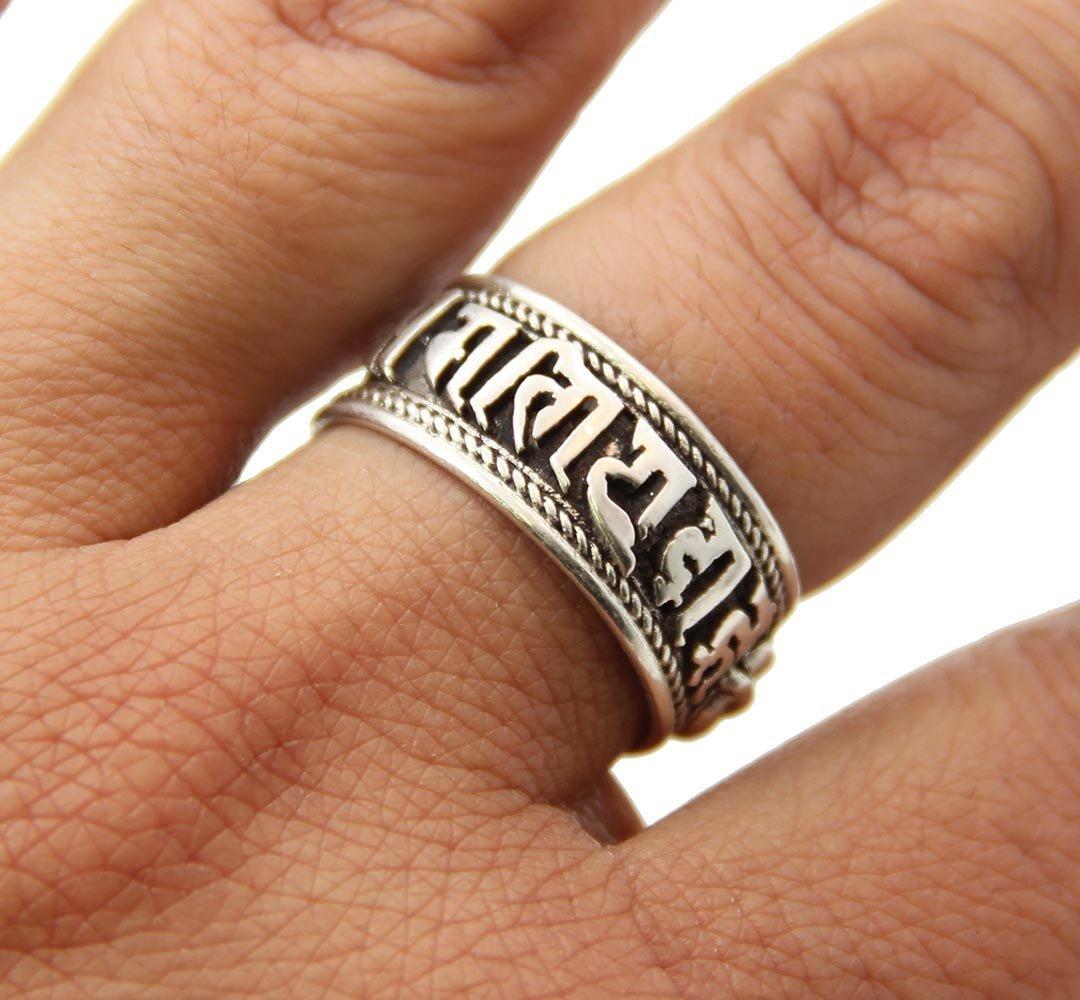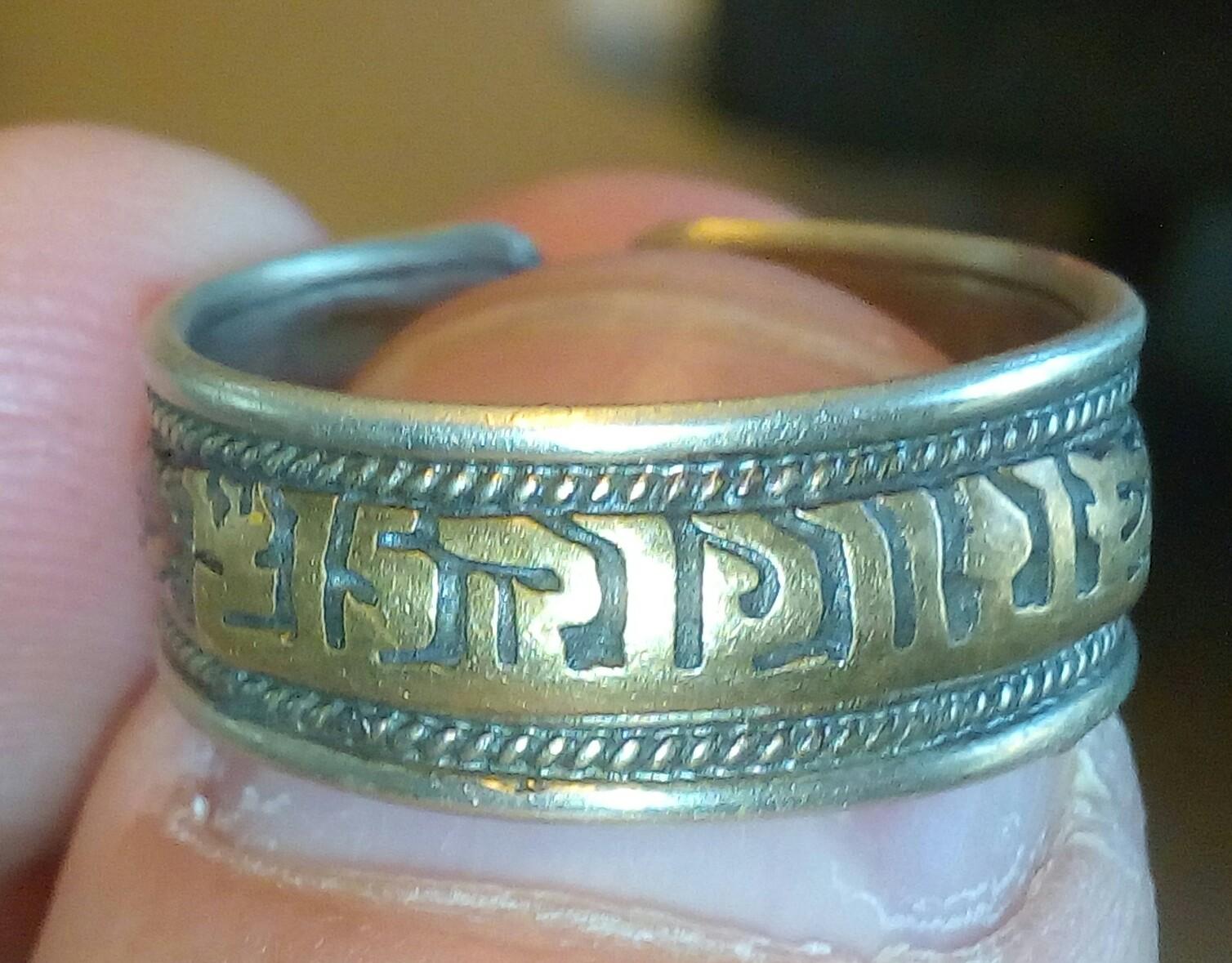
welche Schrift/Sprache auf Ring
kann mir jemand sagen in welcher Schrift etwas auf diesem Ring steht?
(Ggf ist das Foto auch auf dem Kopf.)
2 das erst was mir einfiel: Devanagari
Hatte ich natürlich auch schon mehrmals angeguckt. Auch wenn ich den Ring drehe erkenne ich keine Zeichen wieder.
Vielleicht auch einfach nur ein Phantasie-Muster das eben so ähnlich wie... ausehen soll.  Derartige Fake-Schriften für z.B. Pantasy-Geschichten gibt es in allen Arten, so z.B. auch Fake-Runen. Einfach nur um ein Gefühl "das ist Schrift" zu vermitteln, ohne das der Grafiker, der sich das ausgedacht hat, wirklich die Sprache beherrscht.
Woher stammt denn der Ring? Für mich sieht das irgendwie auch nach einem missglückten Versuch aus, die Tolkienschen Ringrunen nachzubasteln.
Ich würde hier sagen:
1. ziemlich sichser: steht Kopf,
2 das erst was mir einfiel: Devanagari
Catfonts hat eindeutig recht. Der Ring steht kopf. Die Schrift ist auf jeden Fall ein Nordindisches Schreibsystem. Ob es Devanagari oder eine ältere Nagari-Variante ist, kann ich dir anhand vom Foto nicht sagen. Die goldfarbigen Teile sind Schriftzeichen, die von einem Kopflinie runterhängen. Die scharze Teilen dazwischen sind die Weißräume oder Punzen, je nachdem, wie man sie nennen möchte.
Habe die Frage auch, wie empfohlen, auf reddit gestellt und dort kommt mensch zu einem sehr ähnlichen Ergebnis:
Es ist auf dem Kopf, sehr grob gefertigtes Ranjana (Devanagari nicht unähnlich) und inhaltlich ganz klassisch: "om mani peme hung" (wohl Tibetisch und nicht Sanskrit)
Na ja, Mani-Mantra und Lantsa-Schrift (Ranjana) - das geht ja auch 100% zusammen, ist diese Schrift, die ihre Quelle ja in derDevanagai hat ja auch extra für Tibetisch daraus entwickelt. Gut möglich, dass der Ring dann nch einer solchen Inschrift auf einer Gebetsmühle geschaffen wurde.
Und so bin ich dann auf das hier gekommen:
Habe ich noch nie dran gedacht, aber ist ja gut vorstellbar einen Ring mit dem Mantra als eine Art ultramobile Mini-Gebtsmühle mit der anderen Hand ganz dezent immer am Finger zu drehen.
Übrigens hatte ich die Rückfrage noch gar nicht beantwortet:
Der Ring gehört einem Freund, der ihn für kleines Geld auf einem Flohmarkt erstanden hat und aus rein ästhetischen Gründen trägt. Daher und weil innen keinerlei Gravur erkennbar ist, gibt es keine weitere Story zu dem Stück.
Na ja, die weitere Story ist ja jetzt das, was hier herausgefunden wurde, welche Bedeutung das hat, und wie herum das gehört. Auch würde ich mich fragen, ob ich das dem Träger jetzt erkläre oder nicht. Wenn ich z.B. wüsste, das der Träger das nur aufgrund der Ästhetik schön findet und so seine Freude daran hat, weil er darin einfach nur ein Muster sieht, aber von seinem Glauben her Dinge, die mit einer anderen Religion zu tun haben eher ablehnt, dann würde ich es mir zwei mal überlegen, ihm das Teil madig zu machen. Auf der anderen Seite könnte der jenige dir ob der Warnung auch dankbar sein...